――― 今日は鳥海さんがつくられたフォントの原字を
見せていただけるということで楽しみにしてきました。
わー、本当に人の手で書いてあるんですね。すごい!
鳥海 〈ヒラギノ明朝体〉の原字はすべて手書きで書きました。
一文字書くのに45分くらい。
筆ではなくて烏口(からすぐち)をつかっています。
えーと、カラスグチって、言われてもわかんないよね。
これです。この先っちょのところに墨つけて書くの。
今はつかわなくなったんだけども。
――― 今はつかわないんですか?
鳥海 うん、書体制作の道具も、やり方も、
どんどん変わっていますね。
前にね、明朝体をテーマにしたNHKの番組があって、
おれが文字をかいてるところを
ちょこっとだけ撮ったんだけど、
その収録で本当に久しぶりに烏口をつかいました。
久々だったなぁ。緊張したもん。
――― ブランクがあっても、
体が覚えてるっていう感じなんでしょうか。
鳥海 忘れるわけではないけど、
でも前はもうちょっと早くかけたよなと思った。
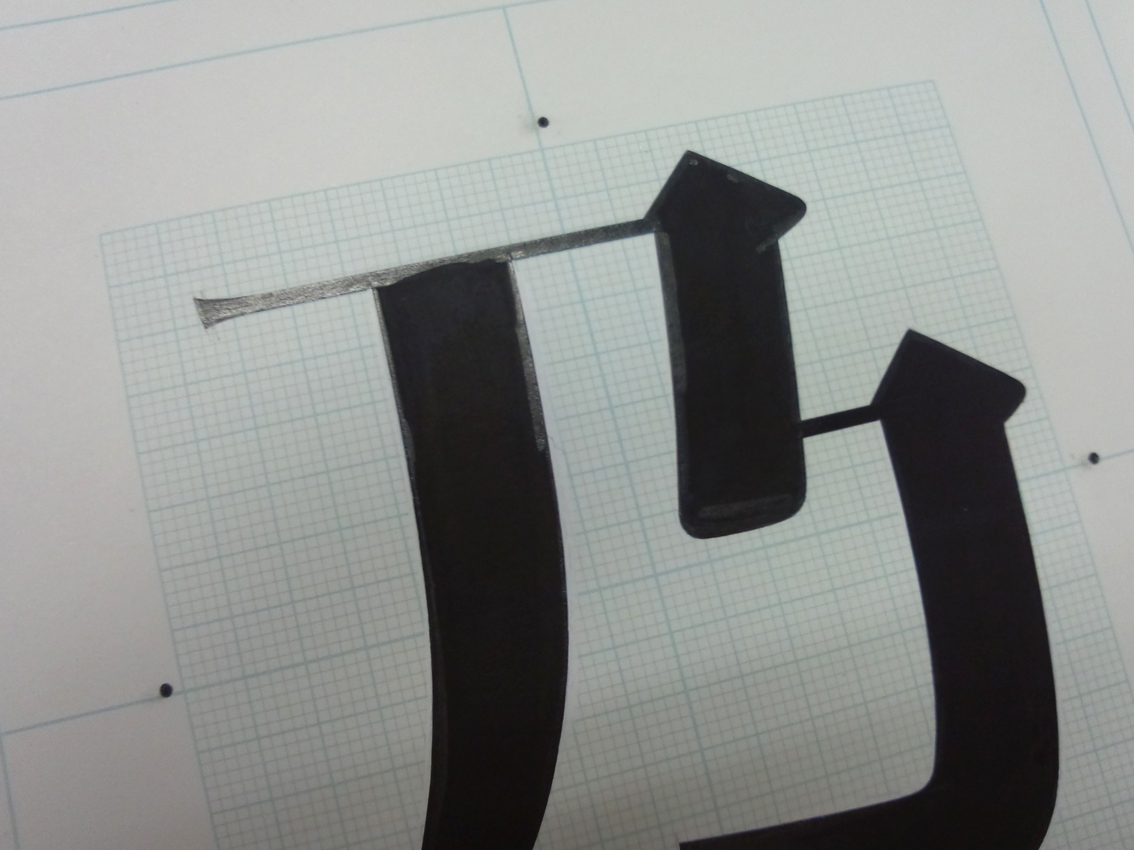
――― これは何で塗ってあるんですか?
鳥海 墨とポスターカラーを混ぜてあるの。
横線がちょっと光っているのわかる?
――― はい、わかります。
鳥海 横線の部分は墨だけをつかっている。
墨だけだとそんなふうに光るんだよね。
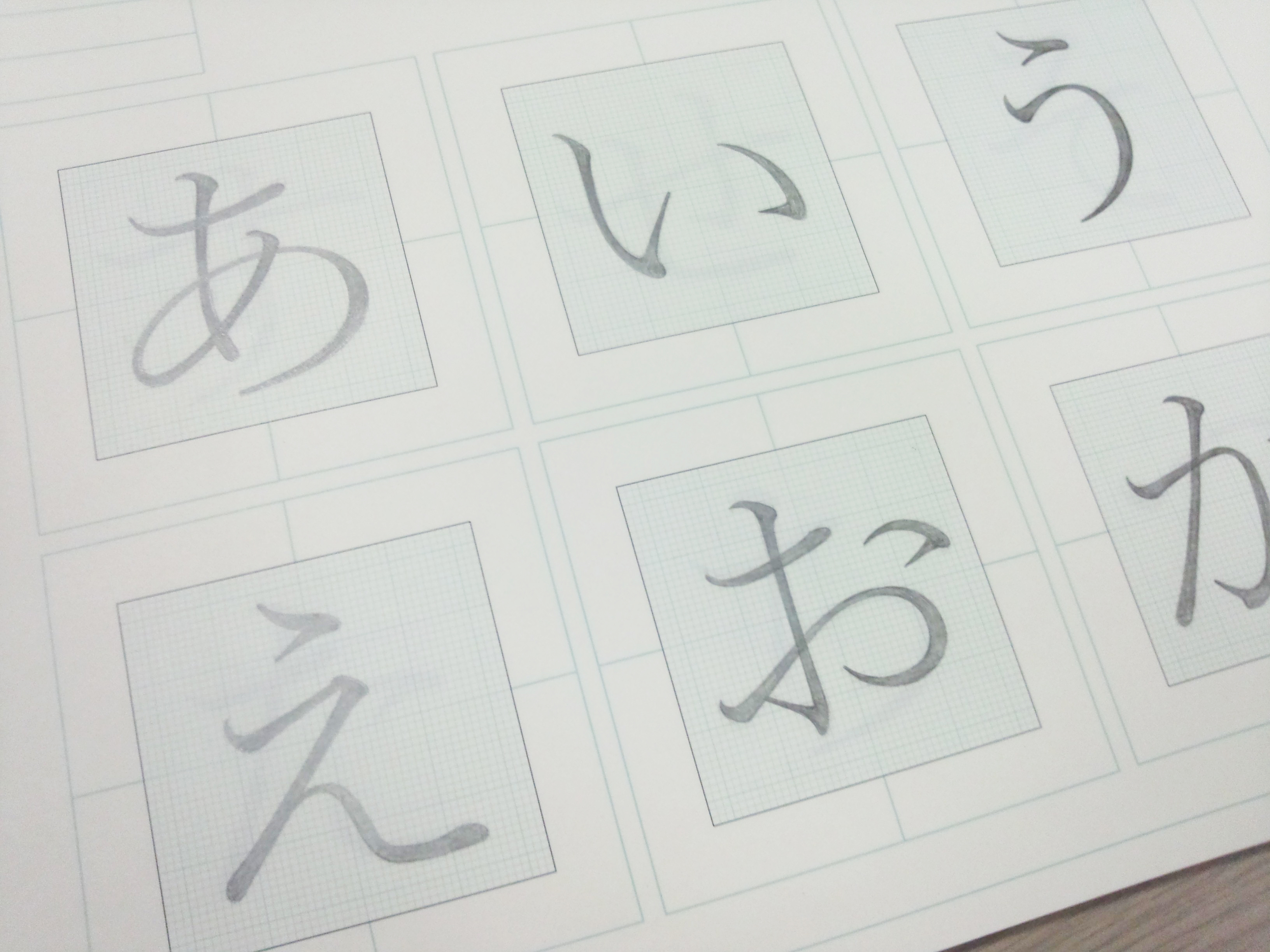
――― (墨を塗る前の段階を見て)この輪郭の部分は何ですか。
鳥海 それは鉛筆。
――― 最初にアウトラインを書くというのが意外でした。
私は文字を読むときに、
自分がその文字になったつもりで見ているんですが、
そのときに心地よく感じる部分というのは、
いわゆるアウトラインじゃなくて、
中心の線から伝わってくる気がするんですけど。
鳥海 えーと、それは、書体の設計と、レタリングの違いだよね。
――― あっ、そうか。そうですね。
鳥海 それと漢字と仮名も、考え方がまったく異なります。
漢字の場合は、四角の中で、
ある要素が均等に入らないとまずいとか、
画数が多くても
下半分に入れなきゃいけないものとかあるから、
おのずと位置が決まってくるんだけど、
仮名はそうじゃない。
自由だけど、そのぶん難しい。
だからこそおもしろいんだよね。
(実際に手を動かして「ま」の字を書きながら)
書きたい文字があるでしょ。
まずこう、イメージになる線を書いて、
それから、肉づけみたいなかんじでデッサンしていく。
――― 今、最初に、すぅっと一本の線を一気に書かれて、
次に「デッサン」といわれたときには
数度にわけてなぞりながら
短い線を少しずつ書き足していくような動きをされました。
私が文字から感じる力点というのは、
やっぱり最初に書かれた全体の線が
軸になっている気がします。
鳥海 うん。きっとそうだと思います。
――― そのイメージになる線というのは
どの時点で決まるんでしょうか。
書いているときにどこかで決まる瞬間があるんですか?
鳥海 頭の中に書きたい文字が見えているから、
それを再現できるように書いてる。
――― すごい!
鳥海 でも人間だから、手がふるえたり、
力が入りすぎちゃったりするでしょ。
あっ、失敗した! って。
そのときは、その失敗した部分だけを
ホワイトで修正していく。
でもね、そのときにはもう、
あるべき線が見えているからわりと簡単なの。
それで、自分の頭のなかにある正解に
いちばん近づいたところでやめる。
――― その、頭の中に正解があるっていう感覚について
伺いたいです。
たとえば私にとっては、自分が書きたいと思う文字と、
実際に書ける文字とは、
能力的にもう全然違うわけですけど、
鳥海さんにとっては「書きたい文字」と「書ける文字」が
ほぼイコールというか…。
鳥海 (しばらく考えて)ある程度はそうかもしれない。
でも書けない文字っていうのは絶対にあるよね(笑)。
時によっても変わる。
おれ、何でも書ける!って 思うときもあるし、
「だめだ…」ってなるときもある(笑)。
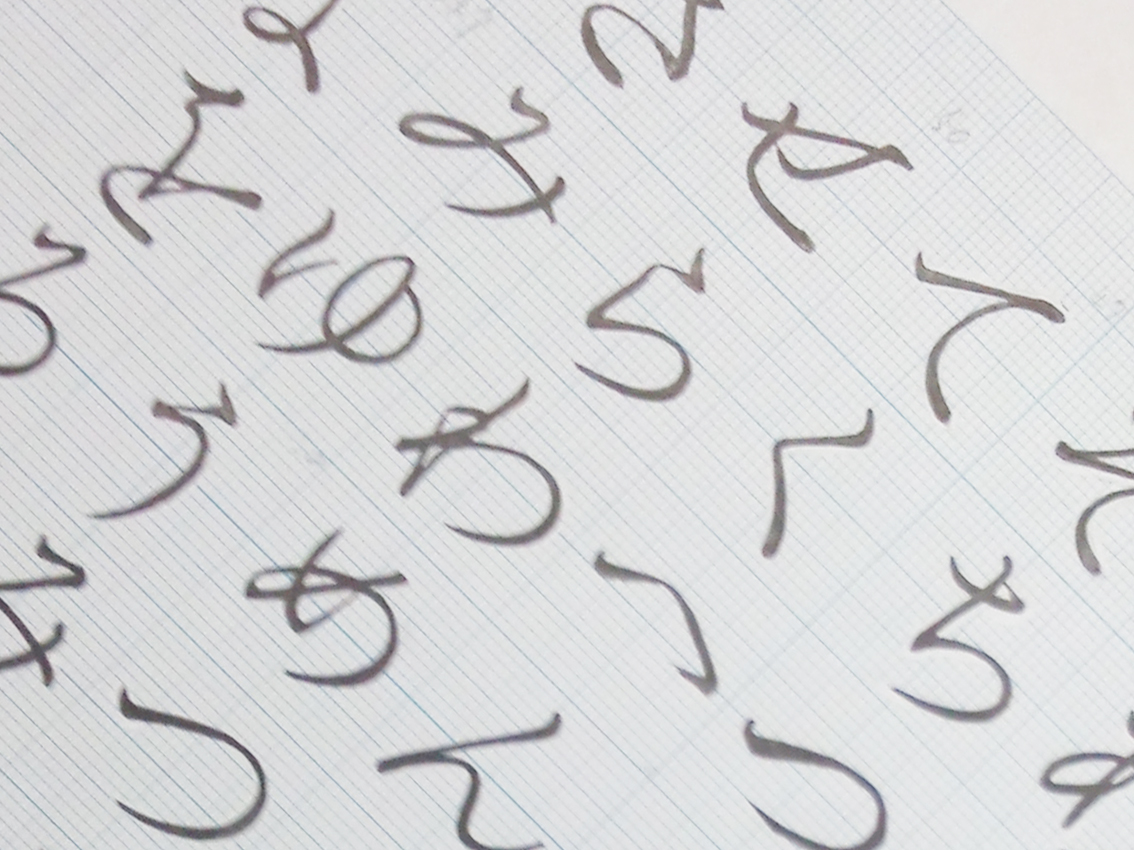
鳥海 これは試しに書いてみたものなんだけど、
この「せ」なんか、いいでしょう。
習作っていうか、こういう作業がいちばん楽しい。
うまく書けたときは「カッコイイ…!」って
自分でみとれちゃったり。
そういうときはすごく幸せ。自分の分身ができる感じ。
この後、スキャンしたデータをパソコンに取り込んで
さらに修正作業をするんですが、
そのときにはあえてもう紙には戻らないようにしている。
正木さんも〈文字の食卓〉の中で
書いていたことだと思うんだけど、
やっぱり言葉っていうのは、文字の連なりであって、
前後に続く文字との関係っていうものが
すごく大事だと思っていて。
だから今はかなり早い段階で、
組んだ状態をチェックするということをやっている。
全部手書きでやっていたころは難しかったけど、
そのためにフォント化するソフトを
うちのエンジニアが作ってくれて、
そういうことができるようになって、
それはもう革命的に役に立っているよね。
四角で完結してたときにはうっとりしてたものが、
実際に文章を組んでみたら
「わー、全然ダメだ」っていうことはままあるんですよ。